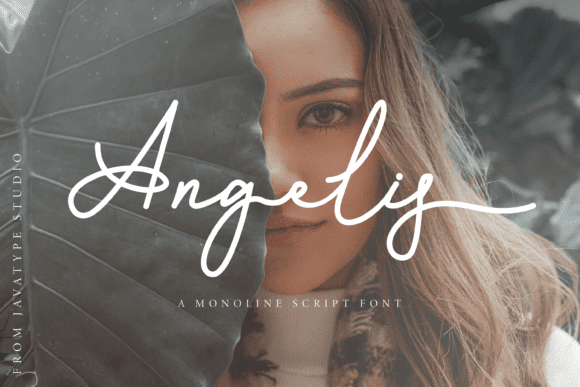
Название: Angelis Font
Angelis это шикарный, изысканный шрифт шрифта, который исходит из изысканности и элегантности.
Его стильные чередования и лигатуры делают этот шрифт идеальным для любого проекта.
Название: Angelis Font
Angelis это шикарный, изысканный шрифт шрифта, который исходит из изысканности и элегантности.
Его стильные чередования и лигатуры делают этот шрифт идеальным для любого проекта.